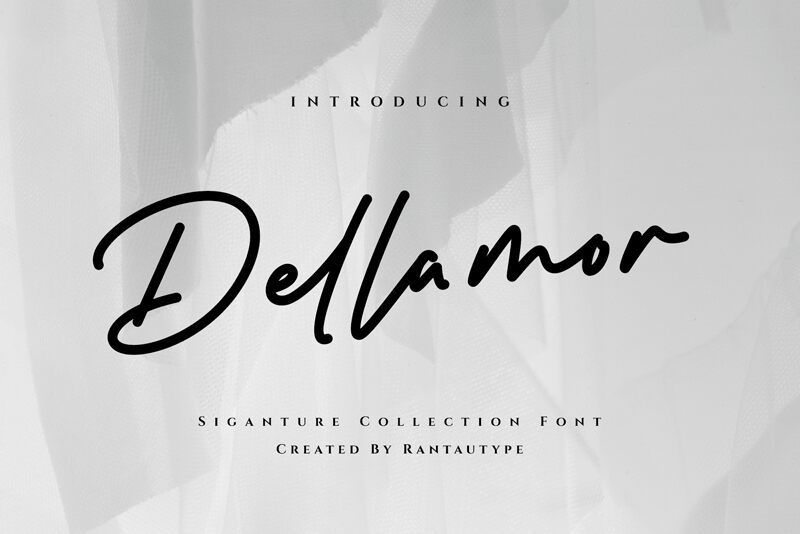
Dellamor od studia RantauType je bezplatné psané písmo s lehkým, romantickým nádechem. Písmena sázejí na dlouhé, plynulé tahy a zaoblená spojení. Díky smyčkovému úvodnímu velkému písmenu a vysokým, vyčnívajícím svislým linkám získává písmo lehký, osobitý rytmus, který působí přirozeně, nikoliv jako strnulé formální písmo.
Hodí se zejména na svatební tiskoviny, branding butiků, obaly kosmetiky, jídelní lístky kaváren nebo citáty na sociálních sítích, kde je potřeba jemný, autorský tón. Jako font zdarma je také ideální pro krátké titulky nebo úvodní grafiky. Použijte jej, pokud chcete, aby název, fráze nebo podpis působily, že byly napsány jedním sebejistým pohybem – zejména v designech, kterým sluší tyto elegantní, protáhlé tvary.